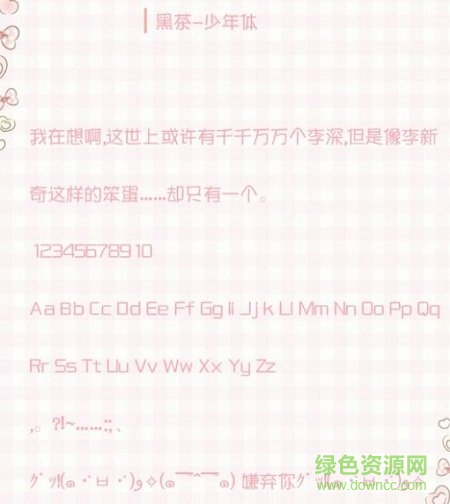
黑茶少年体ttf
黑茶少年体ttf是一款字迹清雅端正的手写字体,有着圆润方形外观,给文字更加饱满大众化的阅读体验,很有幼圆体和卡通字体的风格,快来绿色资源网试试吧!
黑茶少年体字体特色
黑茶少年体将时光装进茶里,将茶装进字里,让它可以永久的流传和回味,扑鼻而来的浓香和怀旧时光,磨成了这款字体,给你午后初阳高照般的温暖体验。
黑茶少年体
黑茶少年体是一款比较好看舒适的少年体,更富有青春活力而不造作,有着不粗的艺术呈现和表达能力,可以广泛使用在艺术设计、包装设计等艺术设计场合哦!